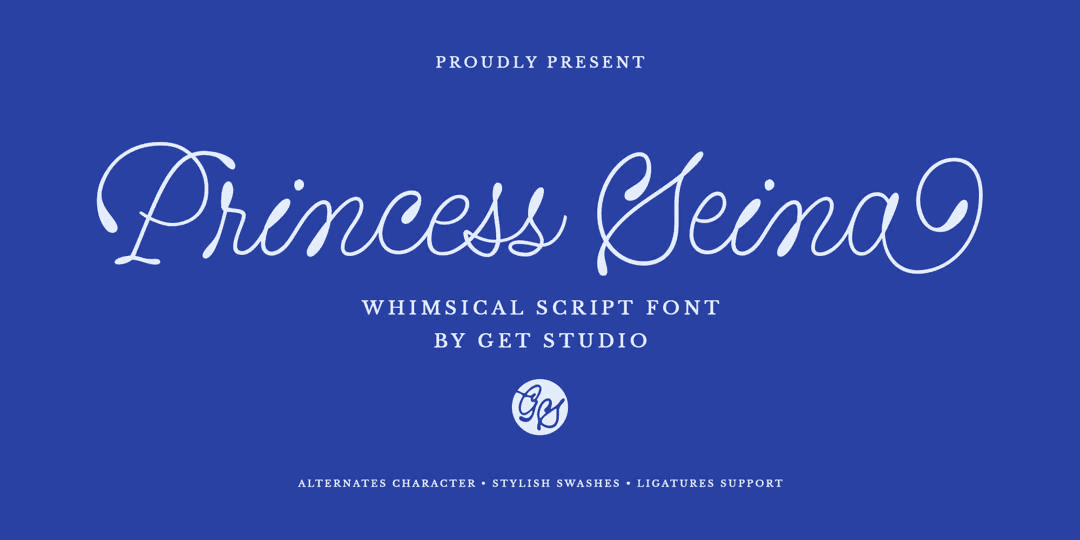
本日雛祭りということでプリンセスなこちら(本来はエンプレスみたいだけど)。風変わりでガーリーなスクリプト。骨格自体はカッパープレートのそれに近いが、モノラインでコントラストがなく、ループが潰れたりストロークの端がぷにょっと膨れて水滴のようになっている。リガチャーは少ないがスワッシュオルタネートは多く、小文字にはループ・カール・水平ストロークが付いたものがある。雰囲気はとにかくポップでガーリー。2ウェイト。